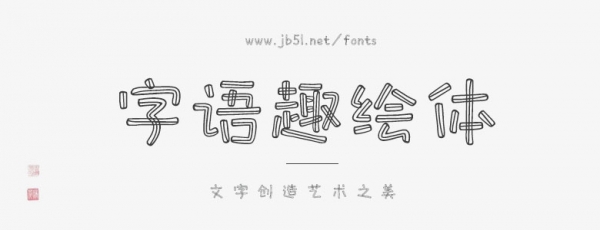
字語(yǔ)趣繪體是一款簡(jiǎn)約可愛(ài)有趣的字體,筆畫(huà)由中空的線條組成,粗細(xì)均勻沒(méi)有筆鋒,結(jié)構(gòu)自由有活力。適用于少兒類(lèi)的書(shū)刊、品牌廣告和產(chǎn)品包裝設(shè)計(jì),綜藝漫畫(huà)用字,以及社交網(wǎng)絡(luò)的個(gè)性化用字。